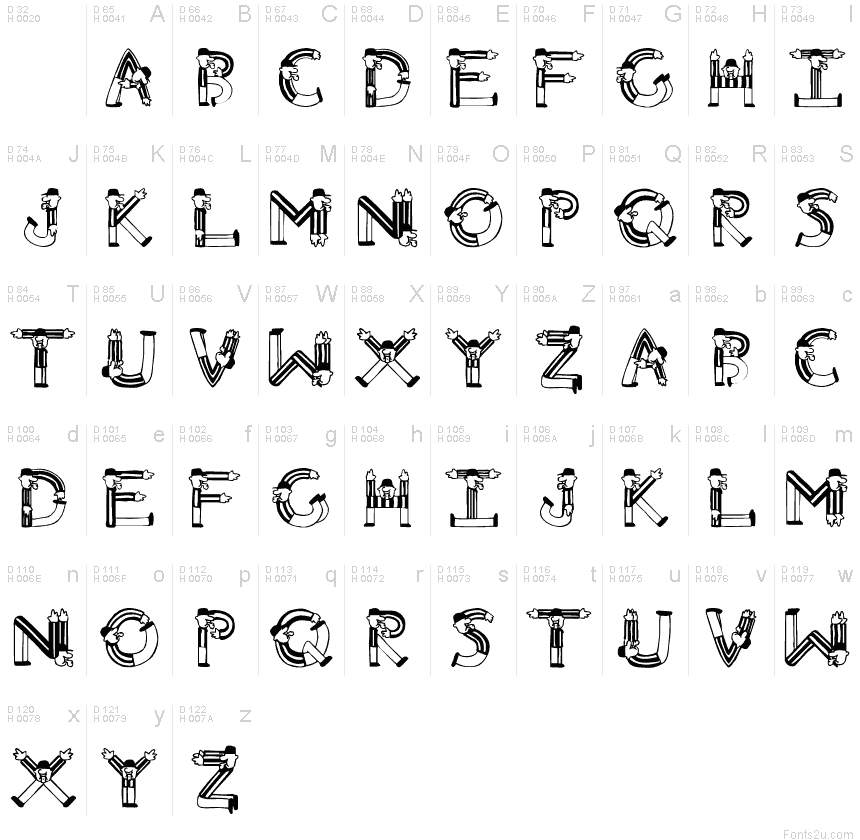
خط Arbitre من Melle DERIEPPE Claude هو خط عرض مجاني بنمط كرتوني يحول كل حرف إلى شخصية صغيرة. تم بناء كل شكل من خطوط عريضة مع أحذية وأيدٍ وأذرع ممتدة تشير في اتجاهات مختلفة، مثل صف من الحكام التعبيريين في منتصف حركتهم. والنتيجة هي حروف حيوية وفوضوية قليلاً، تبدو مرسومة باليد وذات طابع مسرحي، مع حدود سوداء سميكة ومساحات داخلية مشرقة تطلب ملئها بالألوان والقوام.
باستخدام Arbitre، لا تكتفي عناوينك بالتحدث فقط، بل تبدأ في التفاعل. يتألق هذا الخط المجاني على ملصقات الأطفال، وأغلفة الكتب المصورة، ومنشورات الفعاليات الرياضية، والشعارات المرحة، ودعوات الحفلات، أو في تصاميم قنوات يوتيوب وتويتش حيث ترغب في إضافة الحركة والفكاهة بلمحة واحدة. استخدمه بحجم كبير للحصول على أقصى قدر من الشخصية، وقم بدمج Arbitre مع خط "بلا زوائد" (sans serif) هندسي ونظيف للنص الأساسي، حتى تظل الحروف المرسومة هي نجمة العرض.